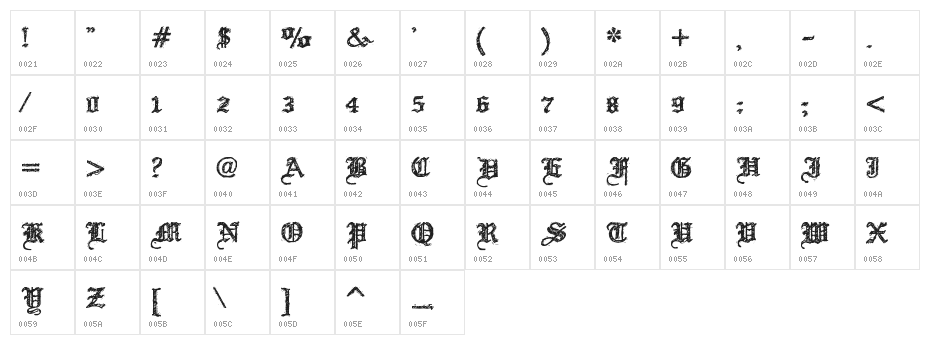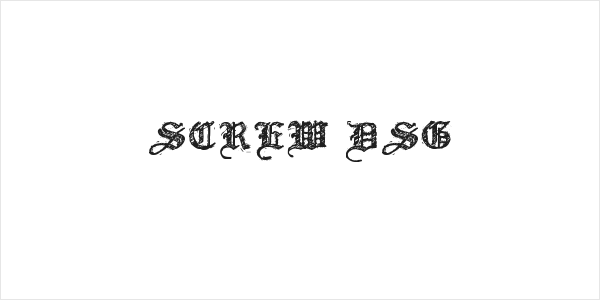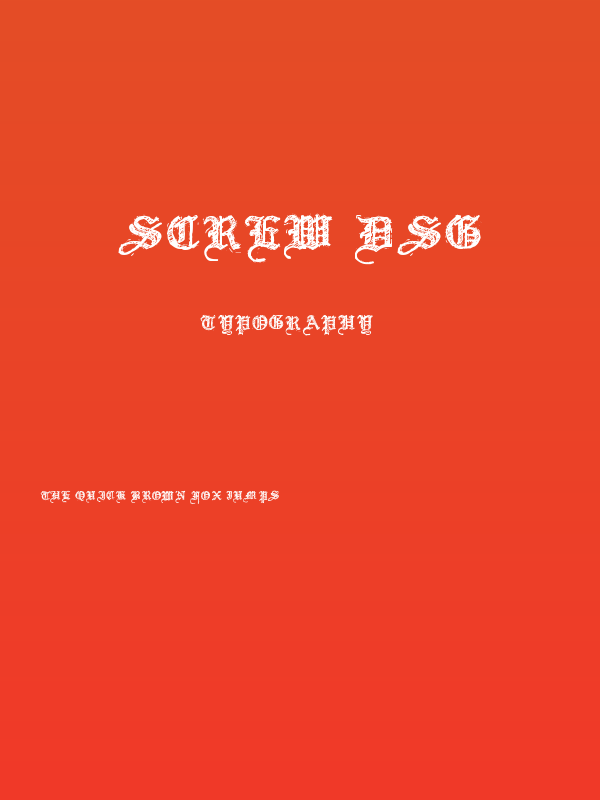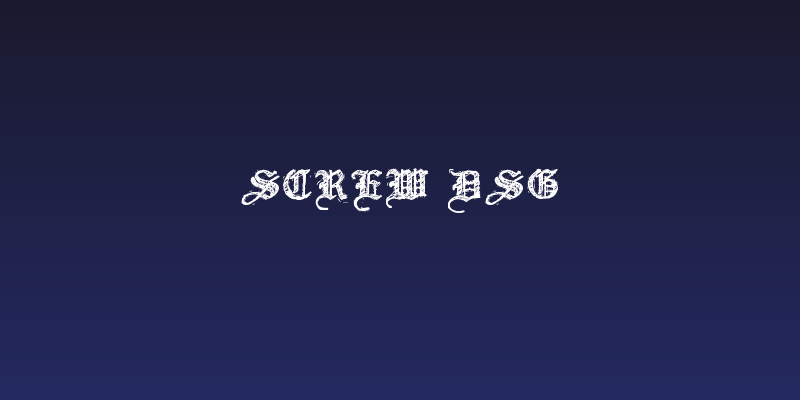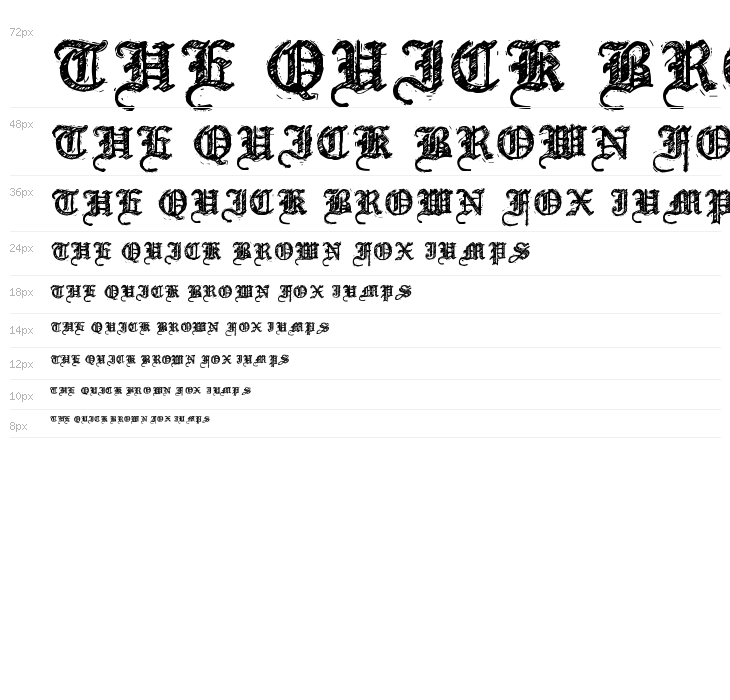
Screw DSG Font
| النمط العام | Vintage |
| حالة الاستخدام | Logos, Headlines, Posters |
| مشاريع مقترحة | Ideal for projects that require a historic or gothic touch, such as vintage posters, themed event invitations, or branding for alternative music bands. |